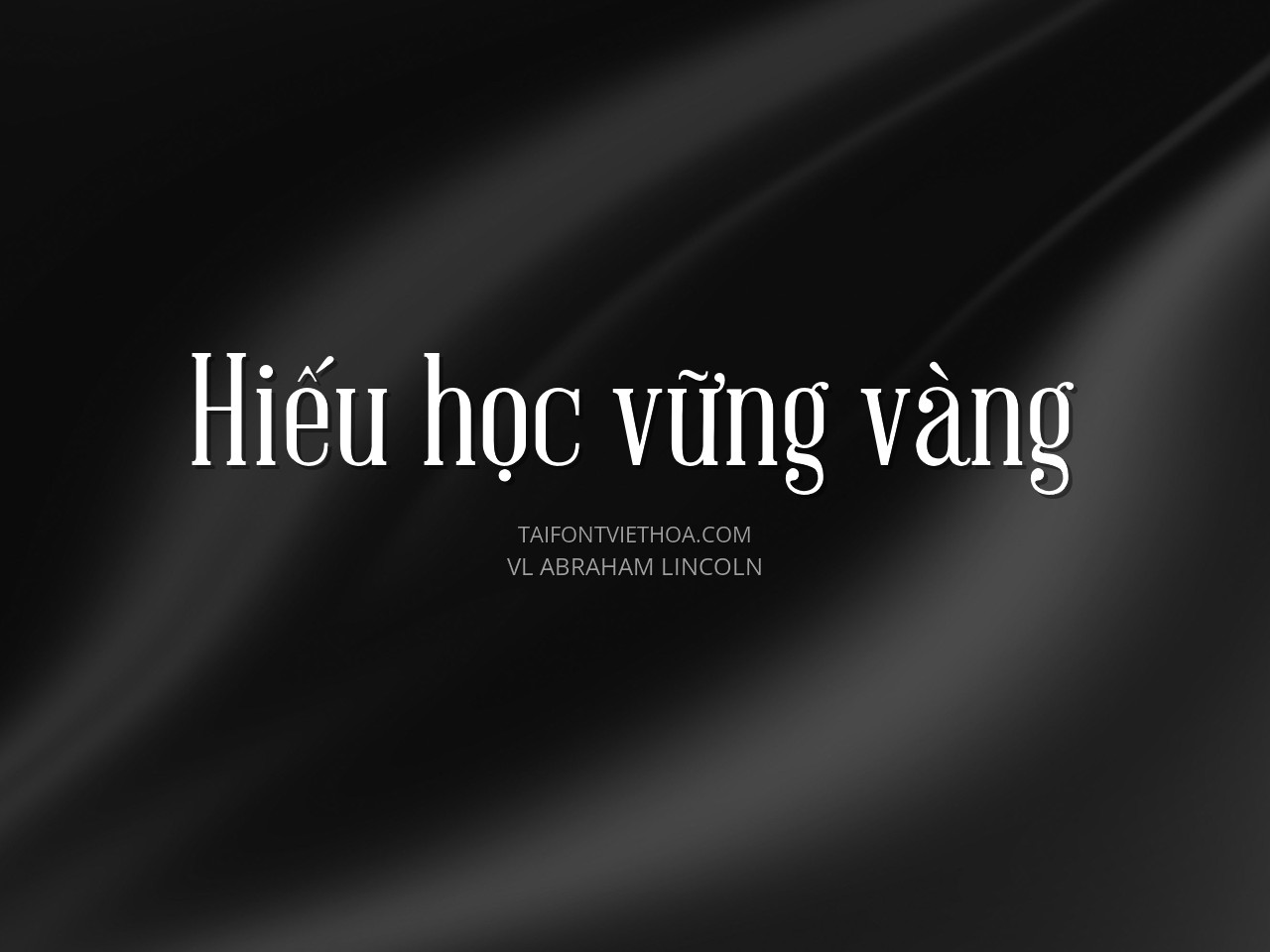
Font việt hóa VL Abraham Lincoln
Giới thiệu về font VL Abraham Lincoln
Abraham Lincoln là một kiểu chữ serif mang phong cách cổ điển, thanh thoát và sang trọng. Font được thiết kế bởi fontfoundry “Lost Type Co-op”, lấy cảm hứng từ các poster cổ điển và phong cách typography truyền thống đầu thế kỷ 20. Phiên bản Việt hóa được thực hiện bởi Font Việt Linh, hỗ trợ đầy đủ tiếng Việt với hệ dấu sắc nét, tinh chỉnh kỹ lưỡng, đồng thời tương thích với hơn 60 ngôn ngữ thông qua bảng mã Latin Extended. Font đã được taifontviethoa.com chọn lọc, kiểm duyệt và thử nghiệm thực tế trong các dự án thiết kế truyền thông và in ấn tại Việt Nam.
Đặc điểm thiết kế và ứng dụng của VL Abraham Lincoln
Font sở hữu dáng chữ cao, thanh mảnh, kết hợp các nét dày – mảnh rõ ràng, tạo ra hiệu ứng thị giác cổ điển nhưng vẫn hiện đại. Kiểu chân chữ cứng cáp nhưng không quá nặng nề, phù hợp cho tiêu đề, nội dung trang nhã hoặc ấn phẩm in ấn cao cấp. Các chữ hoa trong bộ font được thiết kế cách điệu nhẹ nhàng tạo điểm nhấn nổi bật cho logo, tiêu đề và thiết kế nghệ thuật.
VL Abraham Lincoln phù hợp với thiết kế tạp chí, poster cổ điển, bao bì sản phẩm thủ công, logo thương hiệu sang trọng hoặc ấn phẩm giáo dục – văn hóa. Các ngành nghề lý tưởng: mỹ thuật, thời trang cổ điển, giáo dục, xuất bản, thủ công nghệ thuật và thương hiệu truyền thống.